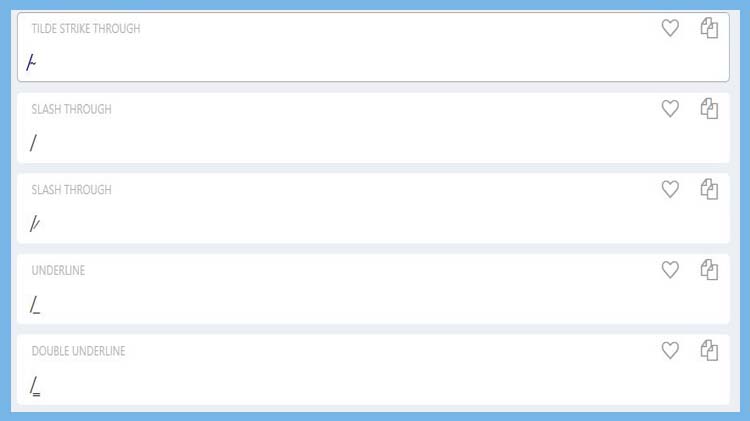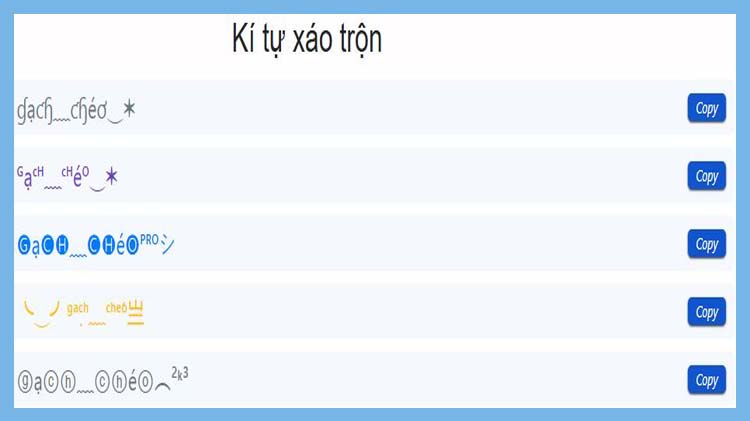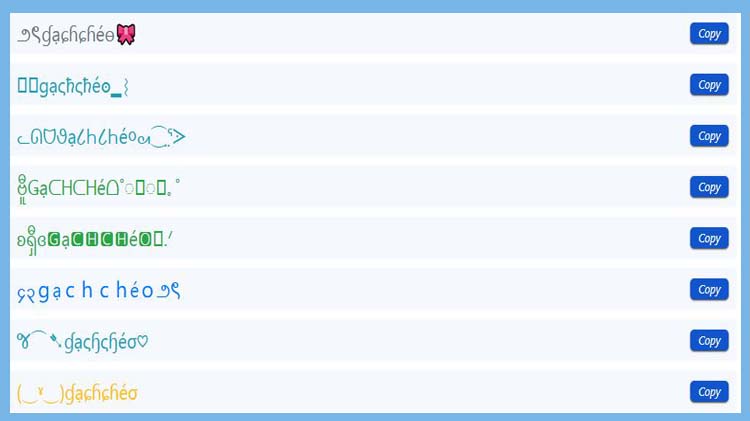
100+ Kí tự đặc biệt gạch chéo ngắn, đẹp và xáo trộn cực độc lạ
Kí tự đặc biệt gạch chéo (/) tuy chỉ là một kí hiệu nhỏ bé, nhưng lại mang sức hút độc đáo và khả năng gây ấn tượng mạnh mẽ với người đọc. Trong bài viết này, chúng tôi sẽ tổng hợp cho bạn 100+ kí tự đặc biệt gạch chéo ngắn, đẹp mắt đến xáo trộn được yêu thích nhất hiện nay.
Bên cạnh đó, MobiFonts cũng sẽ hướng dẫn chi tiết cách tạo kí tự gạch chéo đặc biệt theo phong cách riêng. Hãy cùng khám phá ngay danh sách kí tự gạch chéo cực chất dưới bài viết nhé!
Kí tự đặc biệt gạch chéo không chỉ đơn giản là một dấu phân cách, mà còn có thể giúp bạn tạo phong cách độc đáo cho nội dung của mình. Từ tên hiển thị trên game, nội dung status trên mạng xã hội đến các bài đăng quảng cáo, kí tự này mang lại sự ấn tượng mạnh mẽ. Dưới đây là một số mẫu kí tự gạch chéo phổ biến nhất:
Ký tự |
Tên Unicode |
Mã Unicode |
Mô tả ngắn |
/ |
Solidus (Slash) |
U+002F |
Dấu gạch chéo |
\ |
Reverse Solidus (Backslash) |
U+005C |
Dấu gạch chéo ngược |
/͛⦚ |
Slash + Combining Horn + Two-Teardrop-Bar |
U+002F U+035B U+29DA |
Dấu gạch chéo trang trí với ký hiệu dạng giọt |
/͎͍͐→ |
Slash + Multiple Combining + Right Arrow |
U+002F U+034E U+034D U+0350 U+FFEB |
Dấu gạch chéo kết hợp hiệu ứng và mũi tên phải |
/̊⫶ |
Slash + Combining Ring + Three Dot Punctuation |
U+002F U+030A U+2AF6 |
Dấu gạch chéo có vòng tròn và dấu ba chấm dọc |
/͎ |
Slash + Combining Upwards Arrow Below |
U+002F U+034E |
Dấu gạch chéo với dấu mũi tên bên dưới |
/̾ |
Slash + Combining Long Solidus Overlay |
U+002F U+033E |
Dấu gạch chéo có gạch đè |
/͓̽ |
Slash + Combining X + Combining Line Below |
U+002F U+033D U+0353 |
Dấu gạch chéo có dấu chéo và gạch dưới trang trí |
/҉ |
Slash + Combining Asterisk Overlay |
U+002F U+0489 |
Dấu gạch chéo với hiệu ứng vỡ (như pháo sáng) |
/̶̝̳͔̠̝̮̉ |
Slash + Multiple Combining Symbols |
Dấu gạch chéo bị gạch ngang và hiệu ứng loang màu |
|
/̳ |
Slash + Combining Double Low Line |
U+002F U+0333 |
Dấu gạch chéo với gạch kép phía dưới |
/̲ |
Slash + Combining Low Line |
U+002F U+0332 |
Dấu gạch chéo với gạch chân |
/̷ |
Slash + Combining Short Solidus Overlay |
U+002F U+0337 |
Dấu gạch chéo có gạch ngắn đè lên |
/̴ |
Slash + Combining Tilde Overlay |
U+002F U+0334 |
Dấu gạch chéo với dấu sóng gạch ngang |
Dưới đây là một số kí tự đặc biệt dạng gạch chéo ngắn, phù hợp để bạn dùng trong tên game, biệt danh hoặc văn bản trang trí:
Kí tự |
Tên Unicode |
Mã Unicode |
Ghi chú |
ˊ |
Modifier Letter Acute Accent |
U+02CA |
Nhỏ và nghiêng lên, nhìn như gạch chéo ngắn |
ˋ |
Modifier Letter Grave Accent |
U+02CB |
Nhỏ và nghiêng xuống |
⁄ |
Fraction Slash |
U+2044 |
Ngắn và thường dùng trong phân số |
∕ |
Division Slash |
U+2215 |
Gọn và dùng trong toán |
⧸ |
Big Solidus |
U+29F8 |
Nhẹ cong, nhưng vẫn khá gọn |
Kí tự chữ gạch chéo đẹp là những chữ kiểu được thiết kế phá cách, được tạo nên từ sự kết hợp giữa chữ “gạch chéo” và các ký tự Unicode đặc biệt. Nhờ đó, từng chữ trở nên nổi bật, cá tính và cực kỳ hút mắt, phù hợp để tạo tên game, chữ ký, status hoặc dùng trong tiểu sử mạng xã hội. Nếu bạn muốn sử dụng kí tự đặc biệt gạch chéo đẹp, hãy thử những mẫu sau để tạo hiệu ứng tinh tế hơn:
ミ★ԍạcнcнéo★彡
꧁༒ɡạͼɧ•ͼɧéσ༒꧂
ɠạɔħɔħéøⱭ͞ ̶͞ ̶͞ ̶͞ لں͞
(‿ˠ‿)ɠạɕɦɕɦéσ
જ⁀➴ɠạςɧςɧéσ♡
၄၃gạchchéo౨ৎ
ᓚᘏᗢ૭ạ८Һ८Һé૦ᘛ⁐̤ᕐᐷ
౨ৎɠạɕɦɕɦéɵ🎀
(๑﹏๑//)ջạ☪ɦ☪ɦéℴ
ദ്ദി ˉ͈̀꒳ˉ͈́ )✧ℊạçհçհéօ
Ɓạɔɥɔɥéo☃︎
♰ĞạC̆H̆♰C̆H̆éŎ♰
Ϟɢạċһϟċһéọ⚡︎
亗gạ☾♄☾♄é☯ෆ
㊝GạCHムCHéO모
—̳͟͞͞♥ɕạℭɦℭɦé❍
´꒳`ⒼạⒸⒽⒸⒽéⓄ×͜×
Nếu bạn muốn sáng tạo hơn nữa, hãy thử sử dụng kí tự dấu gạch chéo xáo trộn. Những kí tự này tạo nên sự phá cách độc đáo, khiến nội dung của bạn trở nên cuốn hút hơn. Một số kí tự chữ “gạch chéo” xáo trộn:
ミ★g͜͡a͜͡c͜͡h͜͡×͡×c͜͡h͜͡e͜͡o͜͡★彡
亗𝓰ạ𝓬𝓱×͡×𝓬𝓱é𝓸⁀ᶦᵈᵒᶫ
🄶ạ🄲🄷×͡×🄲🄷é🄾︵²ᵏ⁹
⳻᷼⳺ɢạᴄʜ×͡×ᴄʜéᴏ☯
🄶ạ🄲🄷×͡×🄲🄷é🄾︵²ᵏ⁴
Những câu hỏi về kí tự dấu gạch chéo thường xoay quanh cách tạo kí tự theo ý muốn cá nhân, cách sử dụng các kí tự trên điện thoại hay kí tự dấu gạch chéo có bị lỗi trên nền tảng nào không. Tất cả những thắc mắc đó sẽ được chúng tôi giải đáp ngay sau đây.
Bạn muốn tạo kí tự đặc biệt gạch chéo cực chất thực ra rất đơn giản. Hãy thử ngay trên MobiFonts với 3 thao tác đơn giản sau: